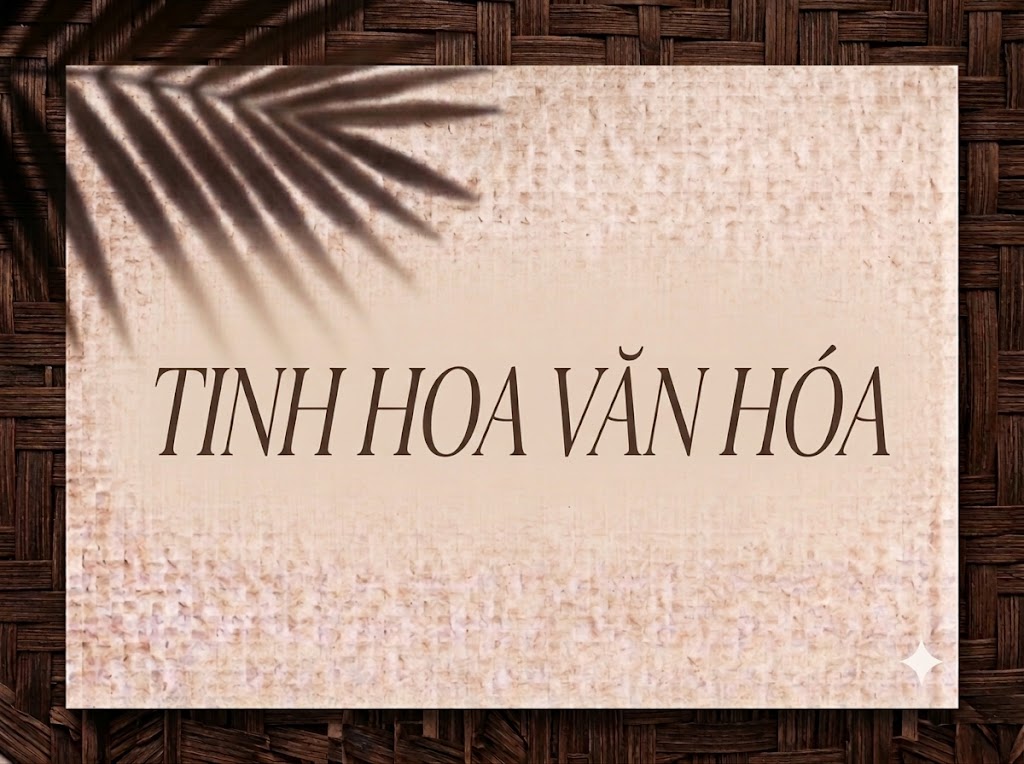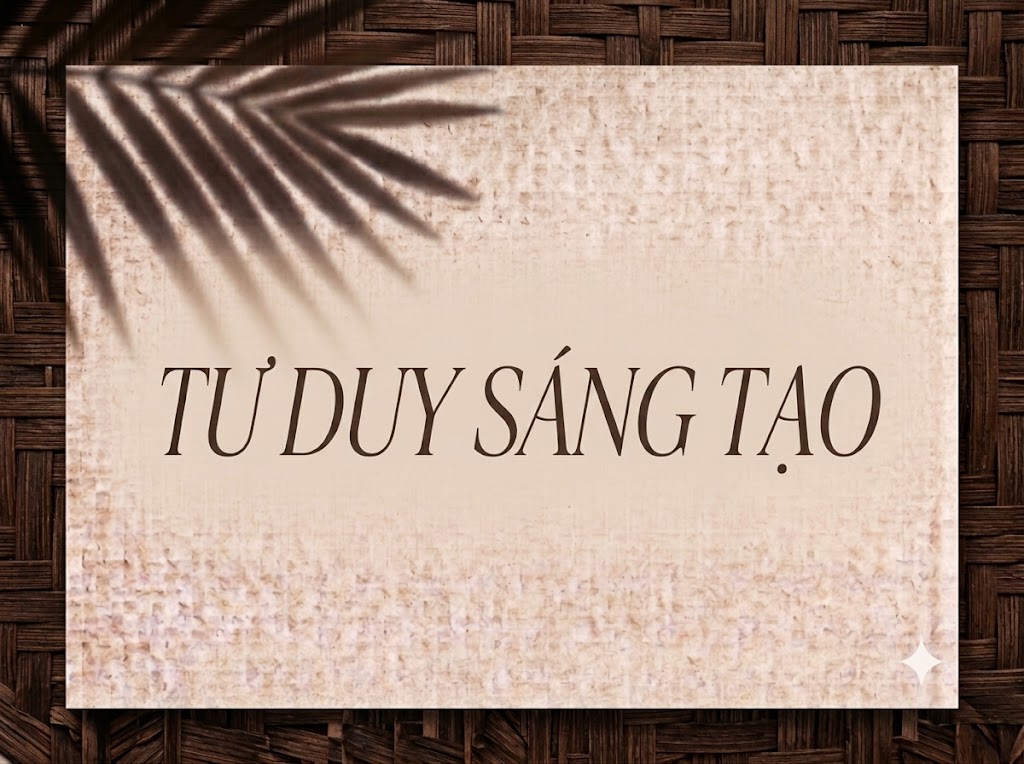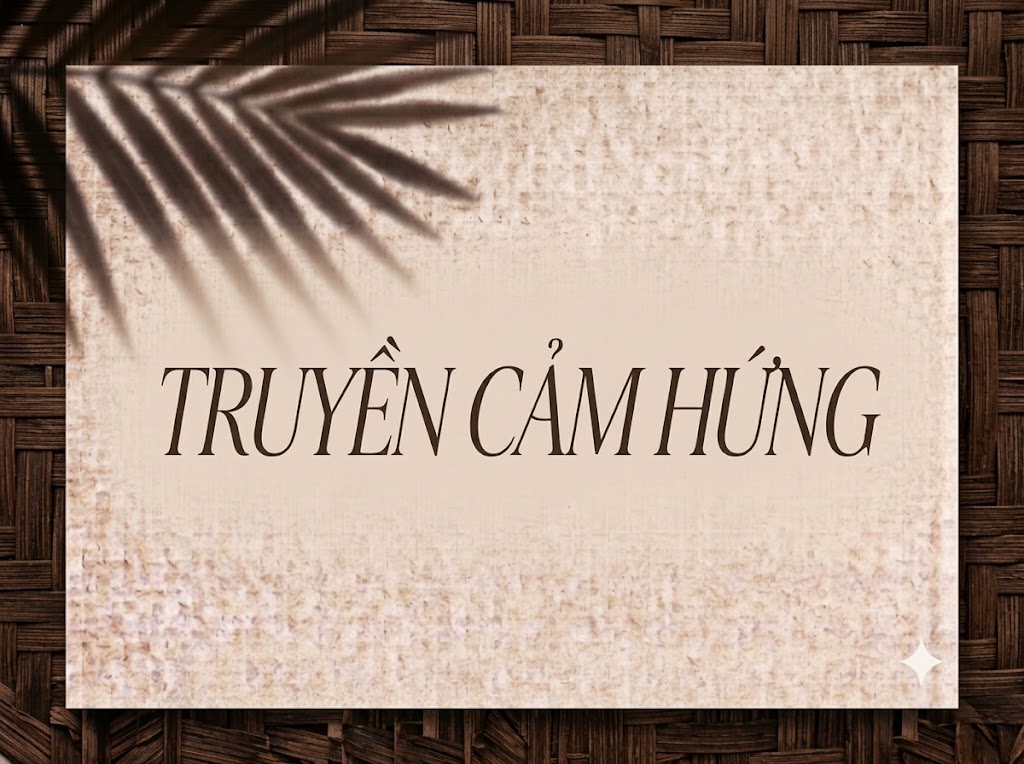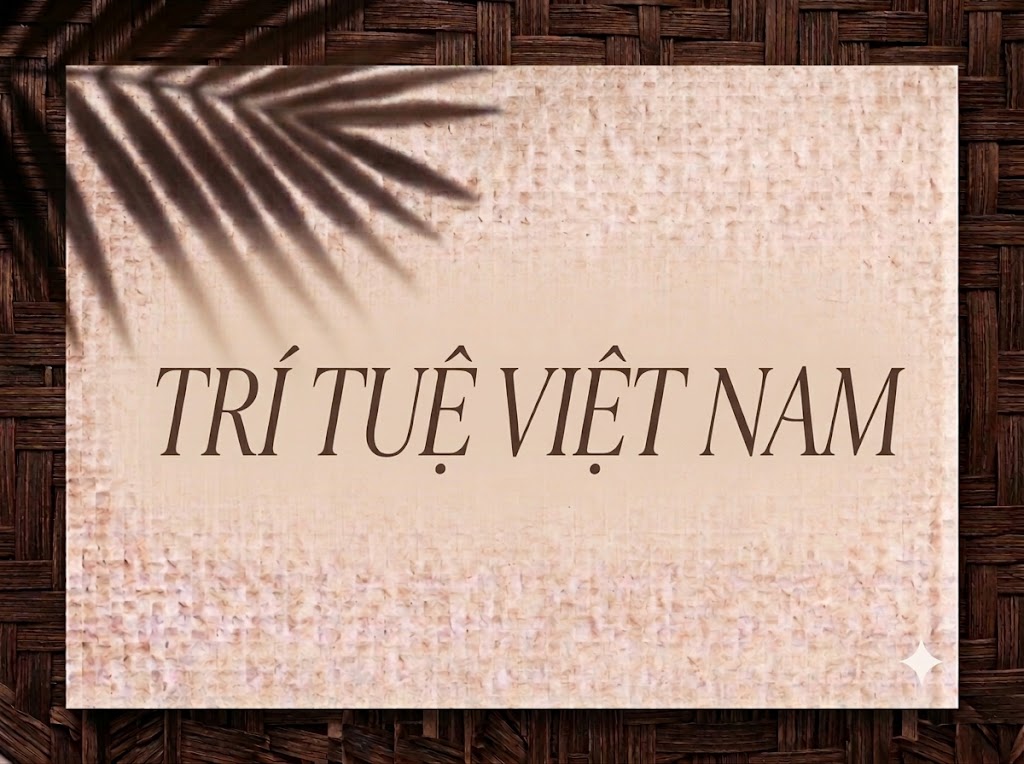
1FTV VIP Calabassas
Trong lĩnh vực thiết kế truyền thông cao cấp, thời trang và xuất bản Tạp chí (Editorial), việc lựa chọn một phông chữ Serif sở hữu thần thái kiêu sa, sang trọng là yếu tố then chốt để định hình dấu ấn thương hiệu. Một dòng tiêu đề ấn tượng không chỉ giúp truyền tải thông điệp ngắn gọn mà còn lập tức thu hút thị giác và nâng tầm giá trị cho toàn bộ ấn phẩm.
Nếu bạn đang tìm kiếm một phông chữ hiển thị mang tinh thần xa xỉ, cổ điển nhưng vẫn tràn đầy hơi thở hiện đại cho logo, bìa tạp chí hay tiêu đề video ngắn, font 1FTV VIP Calabassas chính là sự lựa chọn không thể bỏ qua.
Giới thiệu về font 1FTV VIP Calabassas
Tên phông chữ: 1FTV VIP Calabassas
Được tối ưu chỉn chu về mặt kỹ thuật, phông chữ mang lại khả năng hiển thị mượt mà trên mọi độ phân giải. Bạn có thể tự tin phóng lớn chữ trên các ứng dụng đồ họa chuyên nghiệp hay phần mềm dựng phim mà không lo gặp tình trạng vỡ nét hay răng cưa.
Đặc điểm nổi bật của phong cách thiết kế VIP Calabassas
Sức hút thị giác của font 1FTV VIP Calabassas đến từ phom dáng thanh thoát cùng độ tương phản nét vô cùng tinh tế:
Nét chữ thanh mảnh và kiêu sa: Phông chữ sở hữu chiều cao ấn tượng cùng các nét ngang thanh mảnh, tạo cảm giác thanh thoát, nhẹ nhàng nhưng vẫn giữ được sự vững chãi của dòng Serif.
Chi tiết tạo hình ký tự độc đáo: Điểm đắt giá của VIP Calabassas nằm ở cách biến điệu tinh tế ở các chữ cái như A, E, K, Q, T. Các nét gạch ngang được đặt phá cách cùng phần chân chữ gọt dũa sắc sảo đem lại thần thái cao cấp cho từng câu từ.
Cấu trúc hiển thị đa dạng: Phông chữ hỗ trợ hệ thống ký tự hoa và thường đồng bộ với nhiều nét biến điệu độc bản, giúp các nhà thiết kế dễ dàng kết hợp để tạo ra nhịp điệu tiêu đề thu hút.
Khoảng cách giữa các chữ (kerning) và độ giãn dòng được tính toán chuẩn xác, giúp các đường nét thanh mảnh khi đứng cạnh nhau không bị dính hay rối mắt.
Tích hợp trọn vẹn bộ chữ cái, dãy chữ số 0-9 phom dáng thanh lịch cùng hệ thống ký tự đặc biệt, dấu câu thông dụng.
Bản Việt hóa chuẩn chỉnh giúp bạn hoàn toàn yên tâm thiết kế các văn bản tiếng Việt có dấu mà không gặp lỗi nhảy font hay mất ký tự.
Hình ảnh demo thực tế của font 1FTV VIP Calabassas
Khả năng hiển thị của phông chữ này được tối ưu rất tốt trên nhiều tỷ lệ kích thước khác nhau:
Kích thước nhỏ (12pt – 24pt): Cấu trúc chữ ngay ngắn cùng khoảng hở nội tại rõ ràng giúp câu chữ và dãy số vẫn hiển thị rành mạch trên màn hình di động.
Kích thước lớn (36pt – 72pt): Đây là đất diễn lý tưởng nhất để 1FTV VIP Calabassas phô diễn toàn bộ sự kiêu sa, sang trọng của các nét chân và chi tiết biến điệu tinh tế, tạo tác động thị giác mạnh mẽ cho các dòng tiêu đề chính.
Ứng dụng trong thiết kế đồ họa và làm video
Sở hữu nét cá tính thanh lịch và đầy tính nghệ thuật, font 1FTV VIP Calabassas mở ra không gian ứng dụng vô cùng rộng lớn:
Video ngắn (TikTok, Reels, Shorts): Phông chữ serif dáng kiêu kỳ này hiển thị rất đẹp trên khung hình đứng tỷ lệ 9:16. Nó cực kỳ ăn nhập với các video vlog phong cách sống, review mỹ phẩm, trang sức hay thời trang nghệ thuật.
Ảnh thu nhỏ YouTube (Thumbnail): Lựa chọn tuyệt vời cho các kênh làm nội dung về âm nhạc lofi, acoustic, chữa lành, vlog đời sống cao cấp hoặc review đồ hiệu nhờ giao diện tinh tế và thu hút.
Thiết kế bìa tạp chí, Lookbook và Poster: Hoàn hảo cho các sản phẩm truyền thông thuộc lĩnh vực thời trang xa xỉ, spa, mỹ phẩm hoặc triển lãm nghệ thuật.
Nhận diện thương hiệu phân khúc Luxury: Thích hợp làm logo dạng chữ khối, menu nhà hàng hay khách sạn sang trọng, thiệp mời sự kiện VIP và bao bì nước hoa cao cấp.